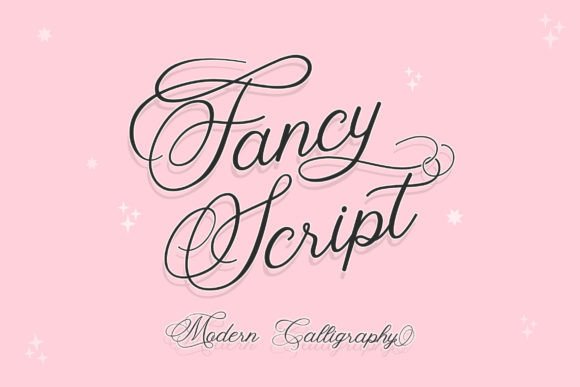
Fancy Script
Fancy Scriptのような高品質の素材をお探しの場合、このプレミアムパッケージはクリエイティブなプロジェクトに素晴らしい選択です。
POD(オンデマンド印刷)製品、結婚式の招待状、またはソーシャルメディアのグラフィックを作成している場合でも、Fancy Scriptは理想的です。